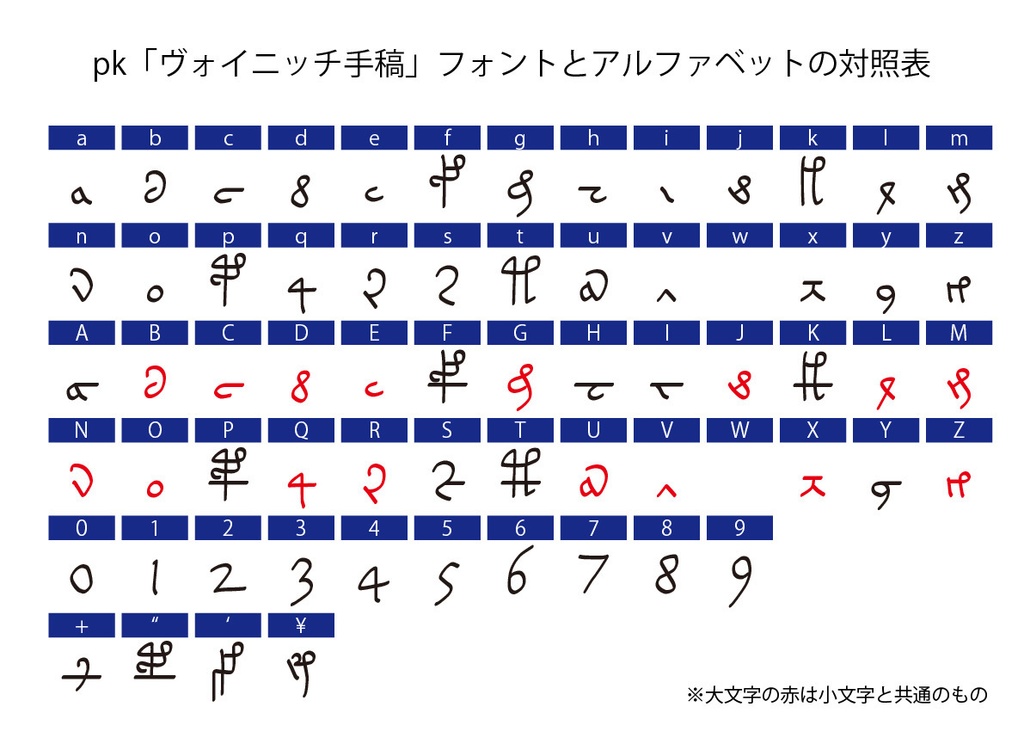
デジタルコンテンツ pk「ヴォイニッチ手稿」フォント
謎の古文書「ヴォイニッチ手稿」で使われている未解読文字のフォントです。 「ヴォイニッチ手稿」(Voynich Manuscript)は1912年イタリアで発見された古文書。謎の文字と奇妙な生物画などが描かれている。これまで多くの人が解読を試みたが未だに解読されていない。 この文書の中で使われている文字をオリジナルフォントとして制作しました。文字の割り振りは、ヴォイニッチ手稿についてまとめたサイト「The Voynich Manuscript」で利用されているフォント「EVA hand1」に準拠しています(ただし「EVA hand1」の文字すべてに対応しているわけではありません)。英語アルファベットの小文字a〜z(wを除く)の25文字、大文字AFHIKOPSTYの10文字、数字0〜9、+(プラス)、"(ダブルクオーテーション)、'(シングルクオーテーション)、¥またはバックスラッシュの4文字にそれぞれヴォイニッチ手稿で使われている文字を割り当てています。 フォントファイルの形式はOpenTypeファイルです。 MacOS VenturaとWindows11での動作確認はしています。 【収録文字】 英語アルファベット小文字a〜z(w除く)、大文字AFHIKOPSTY(それ以外は小文字と同じ)、数字0〜9、+(プラス)、"(ダブルクオーテーション)、'(シングルクオーテーション)、¥またはバックスラッシュ 【データ内容・使用方法】 zipファイルを解凍してください。 OpenTypeファイル pkVoynichf.otf JPGファイル(pk「ヴォイニッチ手稿」フォントとアルファベットの対照表) comparison.jpg テキストファイル readme.txt が収録されています。 pkVoynichf.otfをインストールしてください。 【購入の際の注意点】 商用利用OKです。 使用した場合、ご一報いただけるとうれしいです。Twitterなどで紹介します。 フォントファイルの改変・再配布は禁止です。